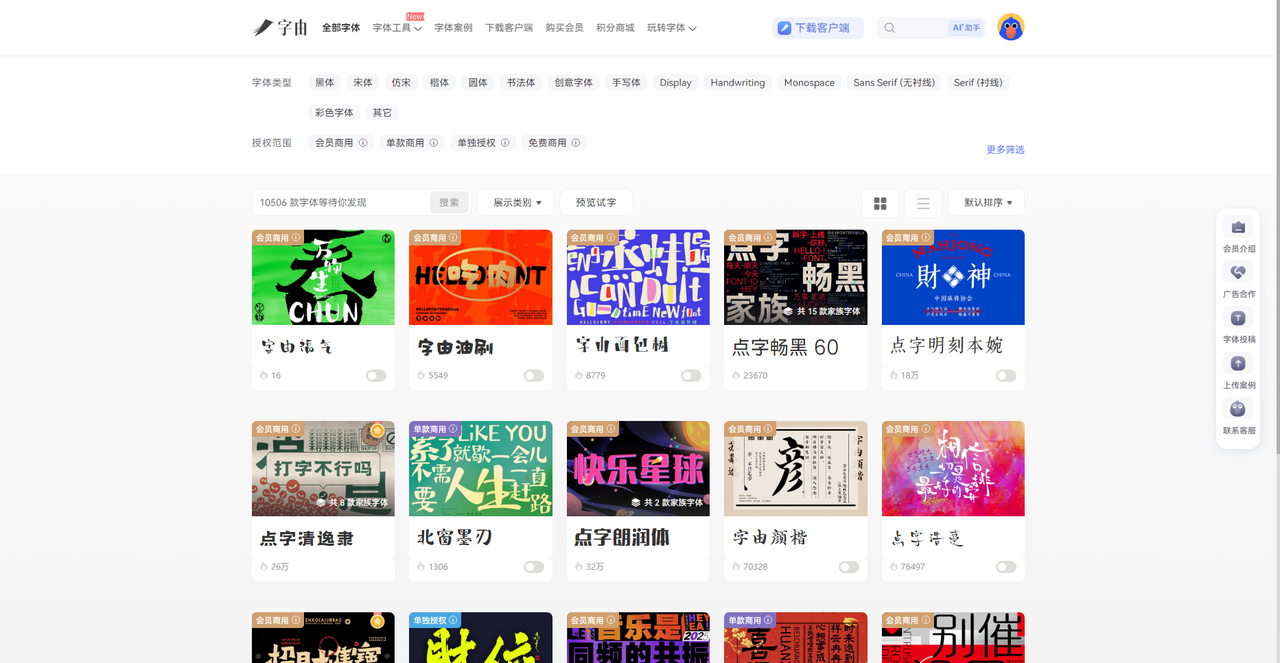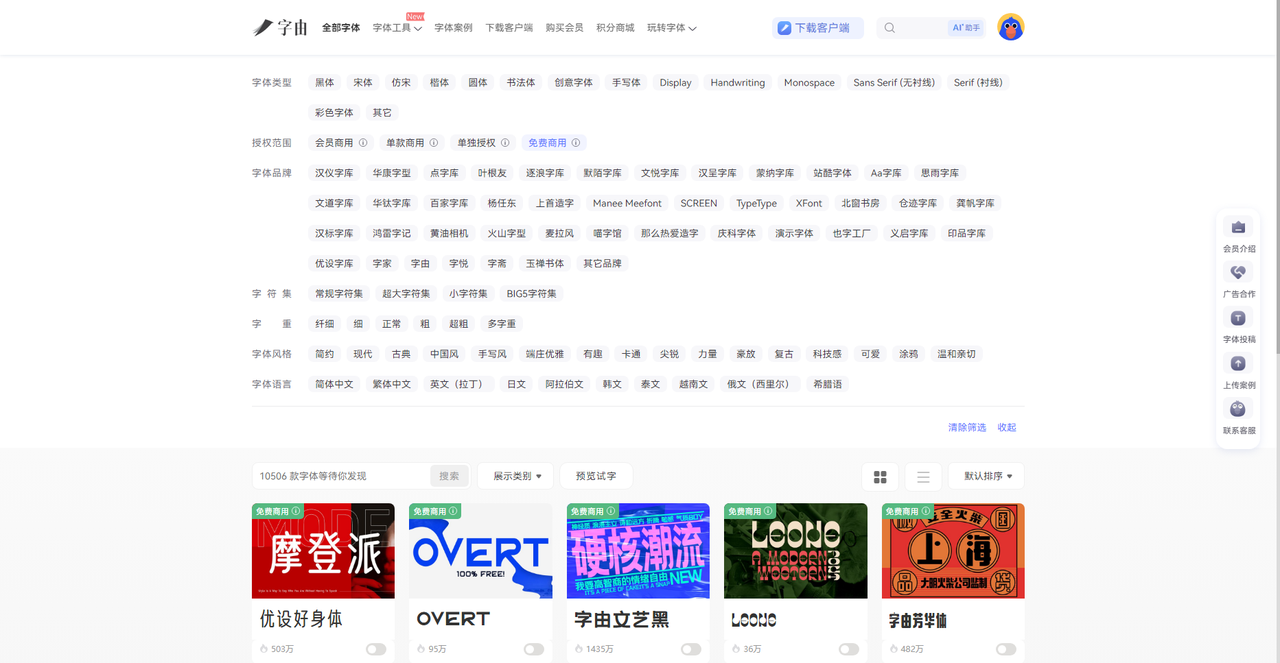
4个免费字库推荐,让你告别字体付费焦虑
如果你也踩过费力找字体最后发现喜欢的那款是需要付费的坑的话,那么这篇会十分适合你。其实,这种“看中了不能用”的尴尬,做设计的都懂。如果想要很好地避开这个坑,最简单、最直接的办法就是找那些能够有专门的免费字体可以下载的网站,省得再踩坑。今天我就把我常用的4 个免费字库分享出来,需要的直接收藏。
第一个要推荐的免费字库是字由。很多人知道字由是字体管理神器,但它本身就是一座巨大的免费字体库。目前字由收录了超过10500 款字体,其中3585 款是免费可商用的。这个体量意味着什么?就是你日常设计需要用到的黑体、宋体、书法体、手写体、艺术体,基本都能在这里找到,而且全部标注了授权类型,用着放心。那么面对这么多字库,如何快速找到免费字体呢?下面我会告诉大家详细的操作:
进入官网或者客户端,点进“全部字体”以后,如果是网页版的话直接按上面给的类型进行筛选就可以,如果是客户端,可以在左侧找到字体分类。
那么我按网页版来的话,具体的分类大概有以下几种:
- 按类型:黑体、宋体、书法体、手写体、Sans Serif、Serif……几乎覆盖所有设计场景
- 按热度:每款字体右下角有使用次数,优先选热度高的,比如“优设标题黑”超1000万次使用
- 按品牌:汉仪字库、蒙纳字库、Aa字库等官方合作品牌专区,品质有保障
按照授权类型的话你一下子就可以筛选出来那些能够免费商用的字体。字由里好用的免费字体不少,但每个人口味不同,我可以推荐我比较喜欢的几款字体:
- 演示悠然小楷:清秀雅致的小楷风格,像古书上的批注。适合做国风海报、读书笔记、传统文化类内容。去年中秋帮朋友做了一张节气海报,用了这款字体,评论区好几个人问“这是什么字体”。
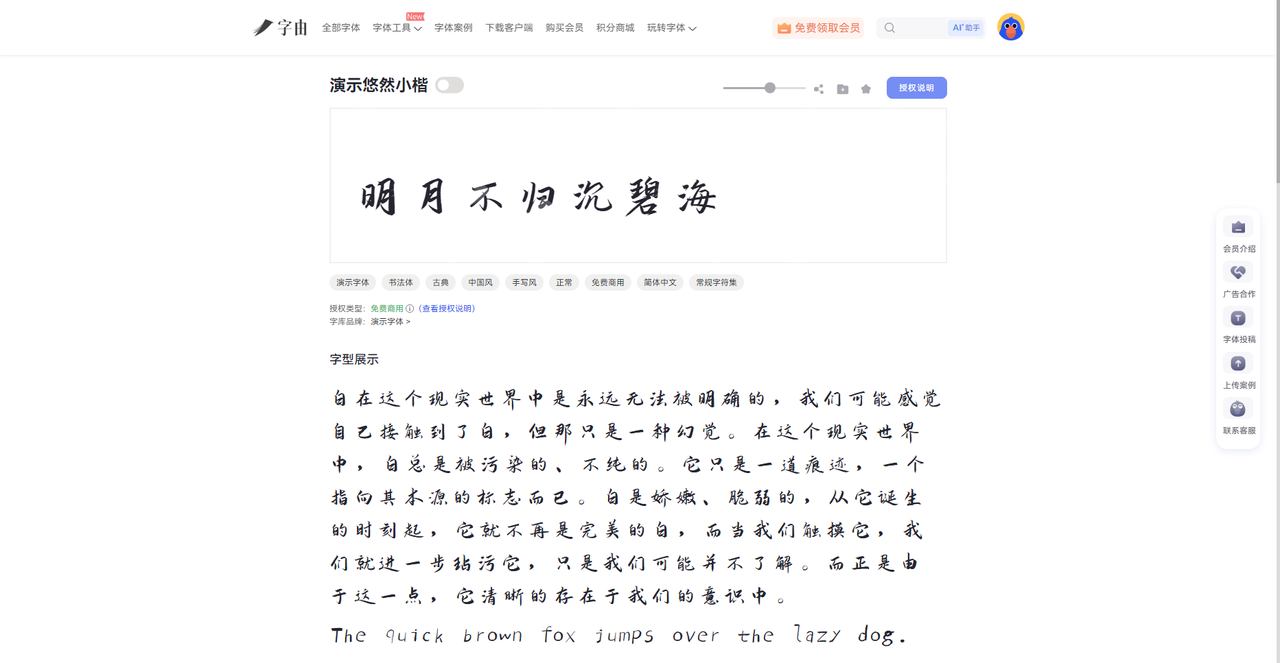
- 重庆山城棒棒体:这款字体最有意思,名字接地气,字形也带着一种朴拙的手工感,像是用刷子蘸着颜料随手写的。适合做地方特色文化、市井生活类的内容。有一次给一家重庆火锅店做菜单,标题用的就是这款。
- 玄宗体:笔画饱满有力,带着唐代书法的气韵。适合做中式婚礼请柬、节气海报、古风设计。
如果你对字体品质有要求,不想在杂七杂八的免费字体里碰运气,可以直接逛字由的品牌字库专区。汉仪、蒙纳、Aa字库、华康这些老牌厂商都在,每一款都拿得出手。商业项目用它们,客户也放心。
2、OpenFont
OpenFont 是一个专注于开源字体的免费字库网站,它的口号是“The Open Source Font Library”(开源字体库)。目前收录了1933款开源字体,全部遵循SIL Open Font License、Apache License 2.0、MIT License等开源协议,可以免费商用。网站支持多维度筛选:可以按语言(支持147种语言)、风格、格式、类别筛选。从截图看,推荐了42dot Sans这款字体,由42dot设计,简洁现代,适合做UI和正文排版。每款字体都有详细的预览和下载按钮,下载前还能看到字体的许可证类型。
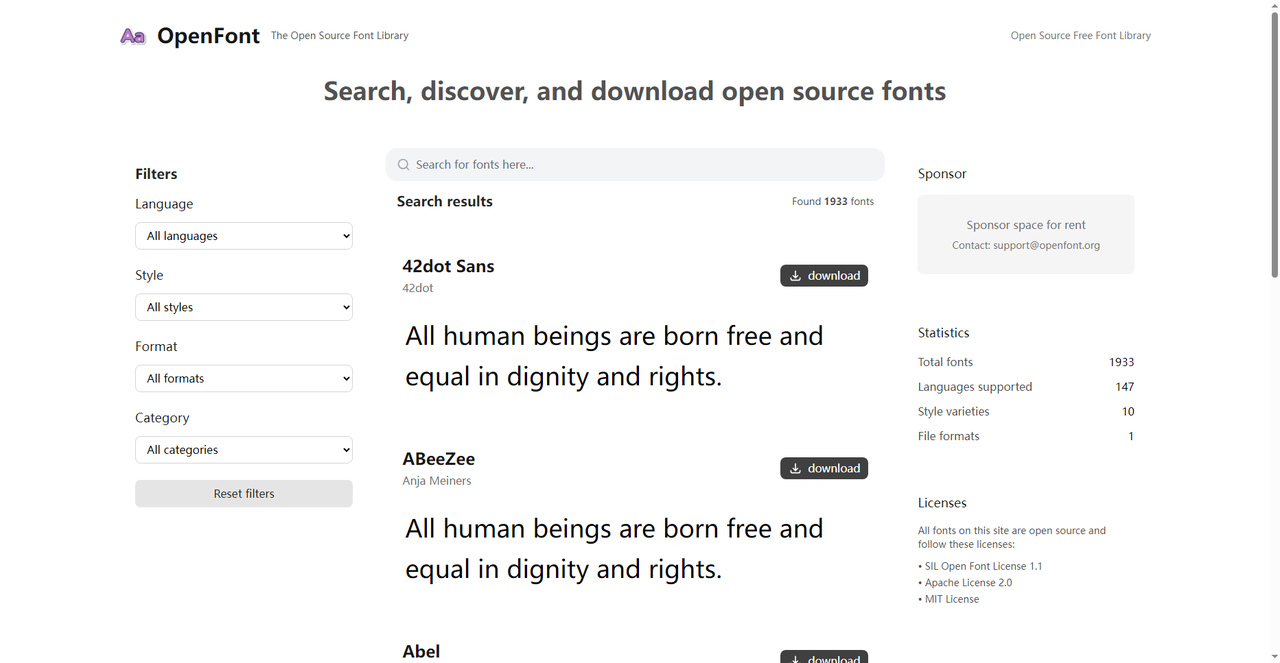
3、Open Foundry
Open Foundry 是一个开源的字体平台,从截图看,它展示了多款精选开源字体:
- M+M Type-1:由Coji Morishita设计
- Archivo:经典无衬线体
- Aileron:现代感强的无衬线体
这个网站的字体数量虽然不如大平台多,但胜在精挑细选,每一款都很有设计感。如果你需要一些有格调、不烂大街的开源字体,这里值得逛逛。每款字体都有详细的设计师信息和下载链接,完全免费。
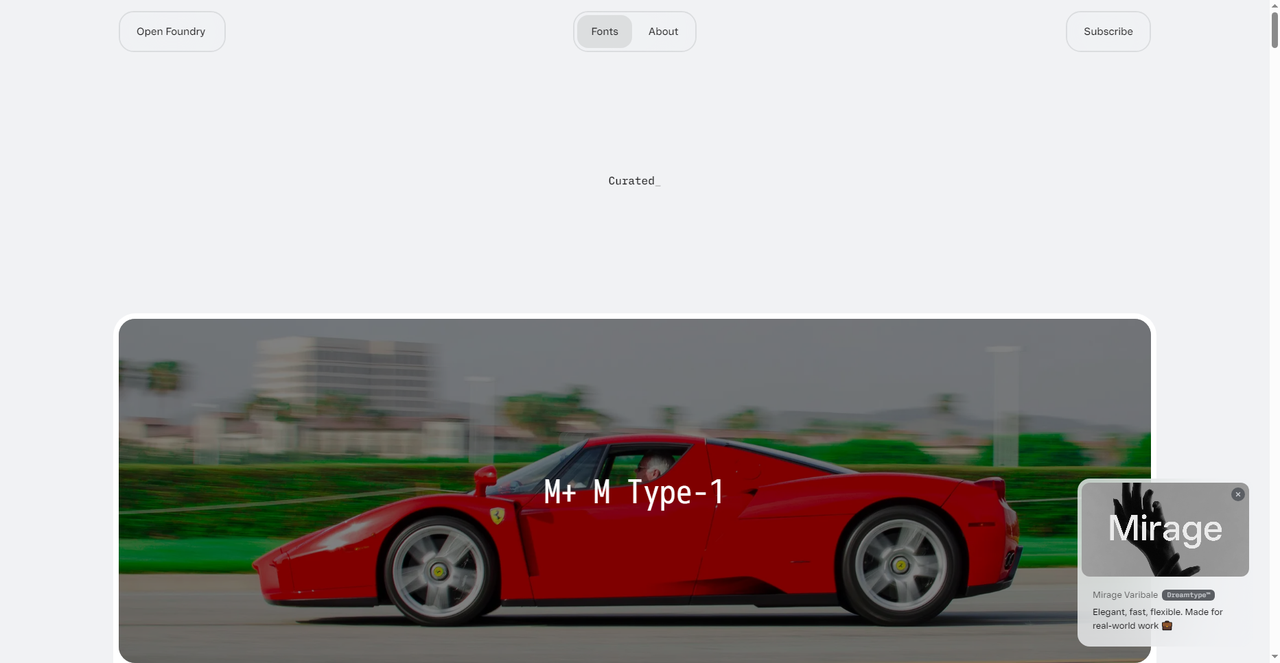
4、FontSpace
FontSpace 是一个老牌免费字体社区,它的首页写着“160,000+ Free Fonts”——16 万款免费字体,是目前全球最大的免费字库之一。这个体量意味着无论你想要什么风格,基本都能在这里找到。网站首页每月会推荐15款手选免费字体,比如截图中的“Masking Renta”“Manline Slabs”等。你可以按“NEW”、“POPULAR”、“RANDOM”、“COMMERCIAL-USE”等分类浏览,也可以直接搜索。每款字体都有详细的预览、下载次数和用户评分。
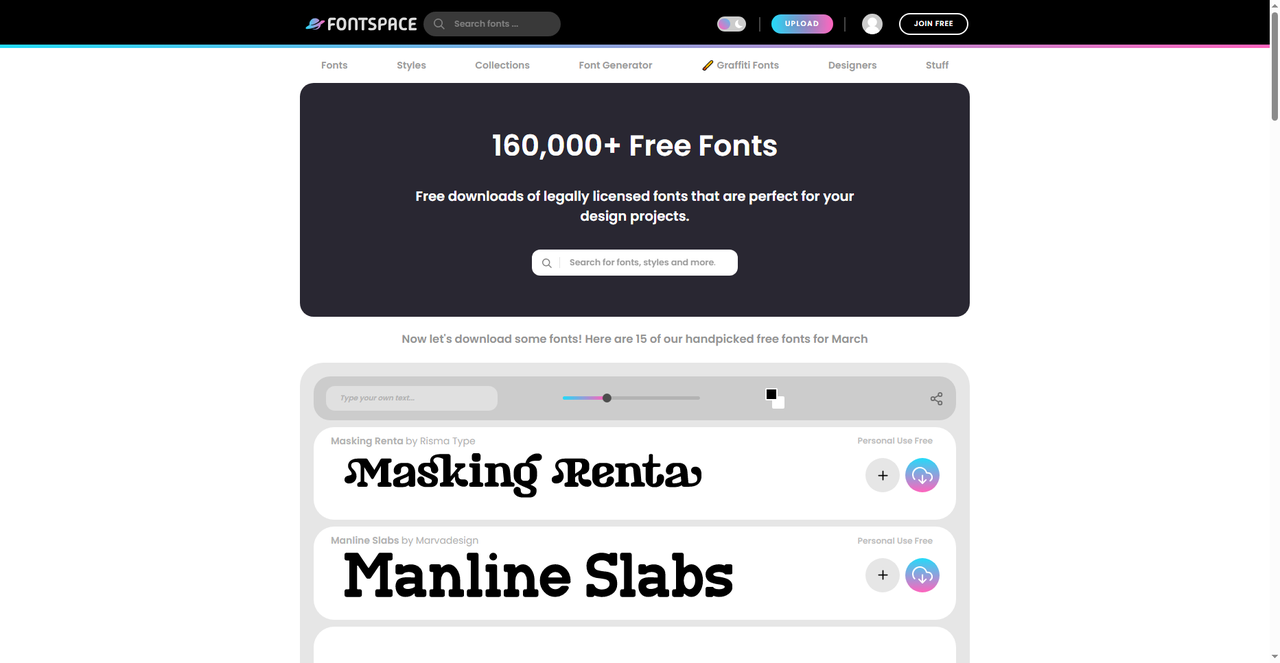
字体付费这件事,说白了就是信息差——你不知道哪些免费、哪些能用,所以才会觉得“好字体都要花钱”。这4 个免费字库,就是帮你把“信息差”填平的。每个字库都在帮你解决同一个问题:让设计不再有付费焦虑。而字由对我来说,是那个把“免费商用”和“管理同步”结合得最好的选择——它不只是给你字体,更帮你把字体管起来,个人云字库、品牌专区,用起来确实省心。如果你也在为字体发愁,不妨从字由开始试试,让设计真正自由。